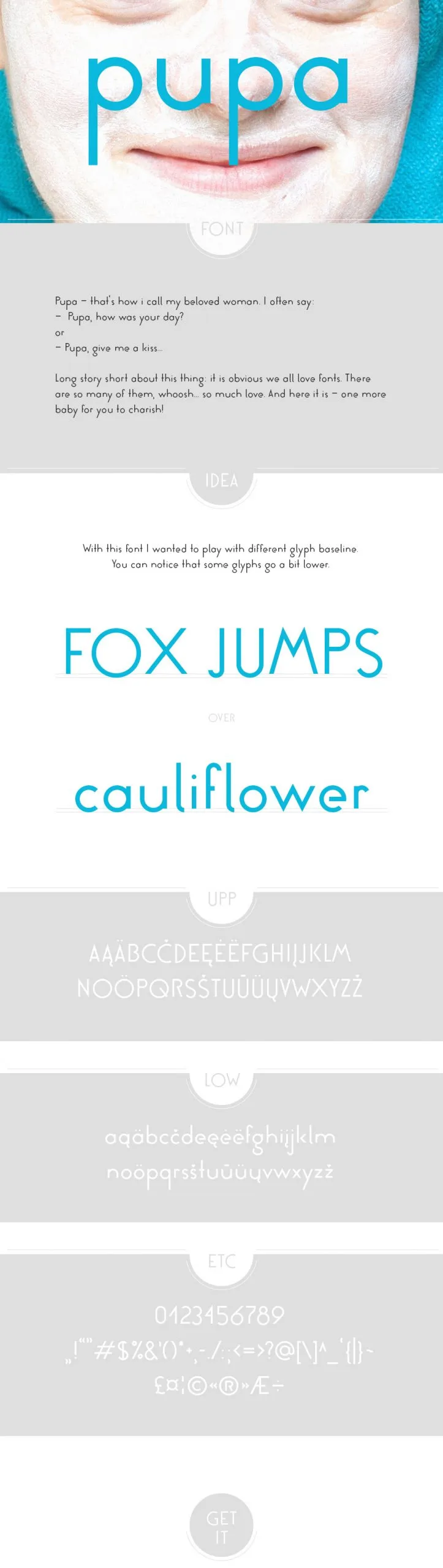
A fonte Pupa é uma escolha ideal para quem busca simplicidade e modernidade na sua tipografia, especialmente nas categorias de letras gerais ou sans serif. Desenvolvida pelo designer Hamilton, a Pupa combina um charme elegante com um toque leve e despojado que torna-a perfeita para diversos projetos digitais. Com linhas retas e formas clean, a Pupa garante legibilidade notável em qualquer dispositivo ou tamanho de fonte. Suas letras são fluidas e versáteis, adequadas tanto para textos informativos quanto para gráficos visuais impactantes. Idealmente, ela se destaca por sua facilidade na leitura, tornando-a uma escolha popular entre profissionais digitais que buscam estilização moderna sem comprometer a legibilidade essencial. Através da Pupa Font, você pode experimentar o equilíbrio perfeito entre clareza e simplicidade em seus projetos. Seja para um site de negócios ou uma página de design minimalista, a Pupa é sua opção ideal.